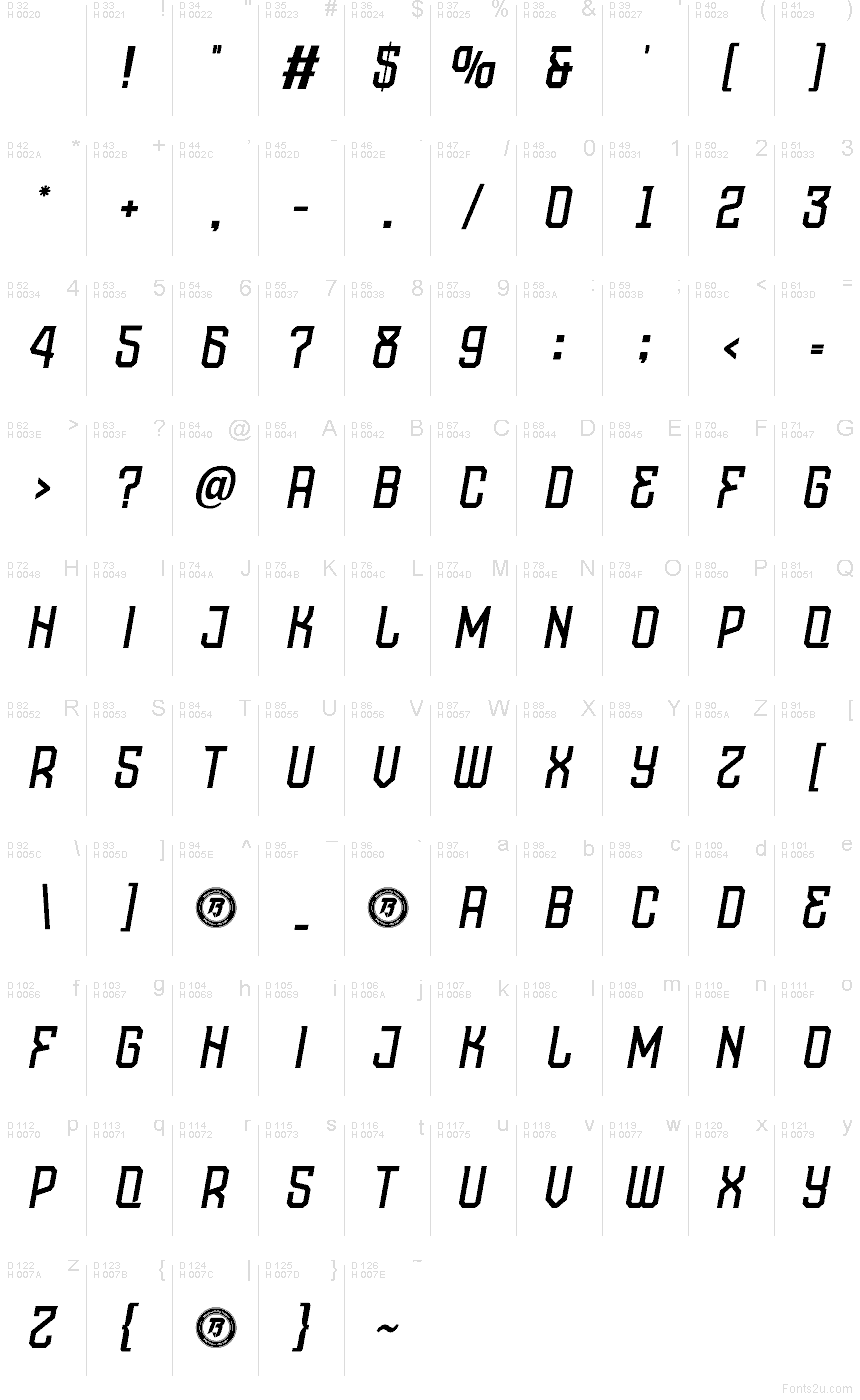
Il font Eindhoven XIV di Muhammad Afif Ersya (Trequartista Studio) è una scelta techno gratuita le cui forme angolari e affilate sembrano ricavate dal vinile e imbullonate su un telaio. La larghezza ridotta e il ritmo costante mantengono una grande agilità anche nelle parole più lunghe, mentre gli angoli netti aggiungono quel carattere tecnico e grintoso senza mai risultare confusionari.
Usare Eindhoven XIV per nomi di team esports, poster sci-fi, livree da corsa, packaging tecnologico, volantini cyberpunk, overlay di gioco e miniature YouTube regala istantaneamente velocità e attitudine. Imposta una leggera spaziatura per far respirare gli angoli e abbinalo a un carattere sans serif neutro per il testo principale: questo font gratuito esprime il massimo potenziale in titoli brevi e d’impatto.